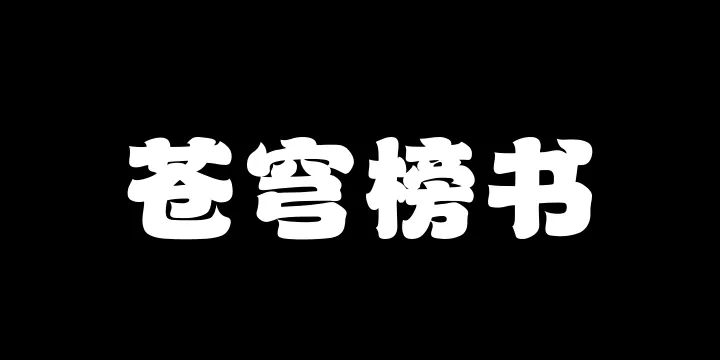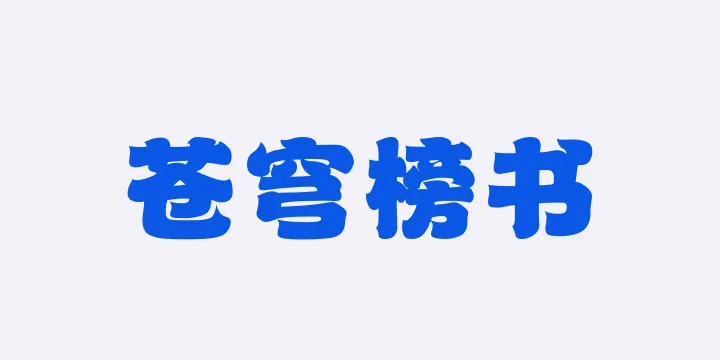
山海苍穹榜书W By 山海字库 商用字体
字体简介: 山海苍穹榜书,是一款擘窠大字榜书字体。包含简繁汉字9169个。该字体雄健有力,霸气外露,在粗细的纵横间,拥有非常规的张力特性。该字体的笔画充满力量感,组合搭配极富强烈的节奏感,融入楷书特点,使字体的视觉效果有力、宽厚、方正,充满了稳重感和设计感。笔画与字形间透露着榜书的古雅和刚劲的特点,在浑厚的同时而又极富张力,桀骜不驯的特性,霸气外露。